Nhiều phiên bản Font Mùa Hè Việt hóa trên Internet chưa được xử lý đầy đủ hệ thống ký tự tiếng Việt, dễ gặp lỗi thiếu dấu, sai ký tự hoặc đường nét bị giảm độ sắc nét khi phóng lớn để in trên hộp quà du lịch, túi giấy và các ấn phẩm sự kiện. Bên cạnh đó, các file font chất lượng thấp có thể ảnh hưởng đến bố cục thiết kế, khiến hình ảnh thương hiệu thiếu sự đồng bộ trong quá trình sản xuất.
Font mùa hè là gì?
Font mùa hè là nhóm các phông chữ mang phong cách phóng khoáng, trẻ trung và tràn đầy năng lượng, thường mô phỏng lại các đường nét viết tay thủ công hoặc các hình khối tròn trịa, vui nhộn. Đặc trưng của dòng phông này là sự linh hoạt trong các nét vẽ, gợi nhắc đến hình ảnh bãi biển, ánh nắng rực rỡ, hàng dừa xanh hay những cơn sóng uốn lượn. Đây là sự lựa chọn phù hợp cho các dự án thiết kế mang tính thời điểm, các chiến dịch marketing cho mùa du lịch, lễ hội mùa hè hoặc các dòng sản phẩm giải nhiệt.
Điểm mạnh của font chữ mùa hè là khả năng khơi gợi cảm xúc hào hứng và sự thư giãn cho người xem. Tuy nhiên, các bộ font quốc tế thường không hỗ trợ đầy đủ bộ gõ tiếng Việt, dẫn đến việc các dấu thanh bị sai lệch vị trí hoặc không đồng nhất về độ dày nét với chữ cái chính. Bộ sưu tập font chữ mùa hè việt hóa được chia sẻ đã được tinh chỉnh Kerning kỹ lưỡng, đảm bảo tính thẩm mỹ và sự rõ ràng khi ứng dụng trên nhiều chất liệu in ấn khác nhau từ giấy mỹ thuật đến kim loại và vải canvas.
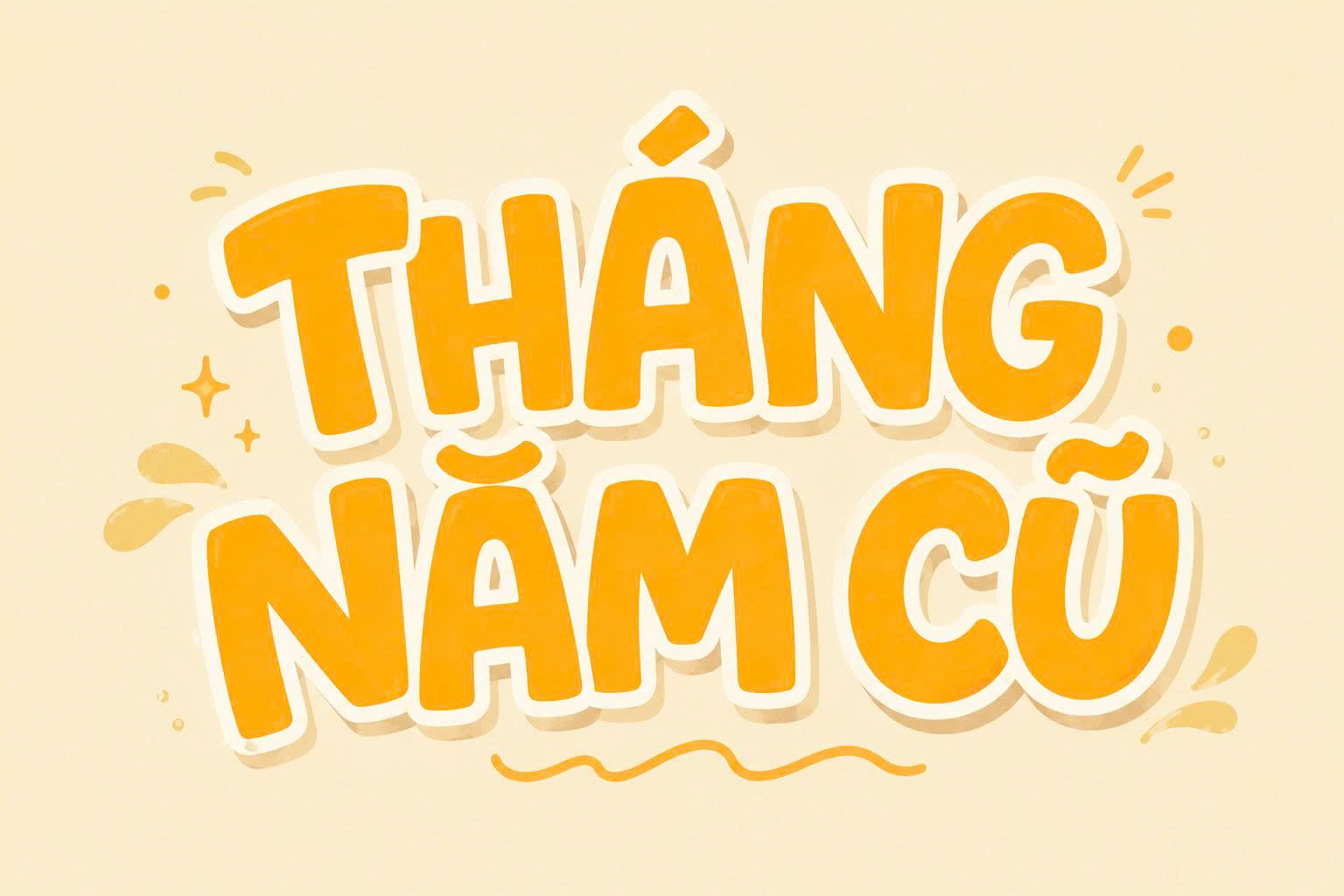
Lưu ý: Font mùa hè thường có nhiều chi tiết uốn lượn nghệ thuật. Khi in ấn trên các chất liệu có độ nhám cao như giấy Kraft, bạn nên kiểm tra độ tương phản màu sắc để đảm bảo các thông điệp truyền tải rõ ràng và không bị nhòe nét.
5 ứng dụng của font mùa hè Việt hóa trong thiết kế và in ấn
Với phong cách trẻ trung, tươi sáng và giàu năng lượng, font mùa hè Việt hóa phù hợp với nhiều thiết kế bao bì, quà tặng và ấn phẩm truyền thông theo chủ đề du lịch, nghỉ dưỡng:
- Thiết kế bao bì thực phẩm và đồ uống mùa hè: Font mùa hè phù hợp để thể hiện tên sản phẩm trên nhãn trà trái cây, nước giải khát, bánh kẹo hoặc thực phẩm đóng gói, giúp thiết kế trở nên sinh động hơn.
- Sản xuất quà tặng du lịch doanh nghiệp: Các slogan ngắn sử dụng font mùa hè khi in trên bình giữ nhiệt, túi vải canvas, nón hoặc vật phẩm sự kiện giúp bộ quà tặng mang phong cách trẻ trung, phù hợp với hoạt động team building.
- Trang trí backdrop và banner sự kiện ngoài trời: Định dạng vector giúp font mùa hè giữ được đường nét rõ ràng khi phóng lớn trên backdrop, bảng hiệu hoặc khu vực check-in sự kiện.
- Thiết kế thiệp mời và voucher mùa hè: Những kiểu chữ mang cảm giác phóng khoáng, vui tươi phù hợp với thiệp mời du lịch, chương trình ưu đãi nghỉ dưỡng hoặc sự kiện thương hiệu.
- Sản xuất tem nhãn decal sản phẩm: Font mùa hè có thể ứng dụng trên sticker, nhãn dán mỹ phẩm, đồ uống hoặc sản phẩm thủ công để tạo điểm nhấn riêng cho bao bì.
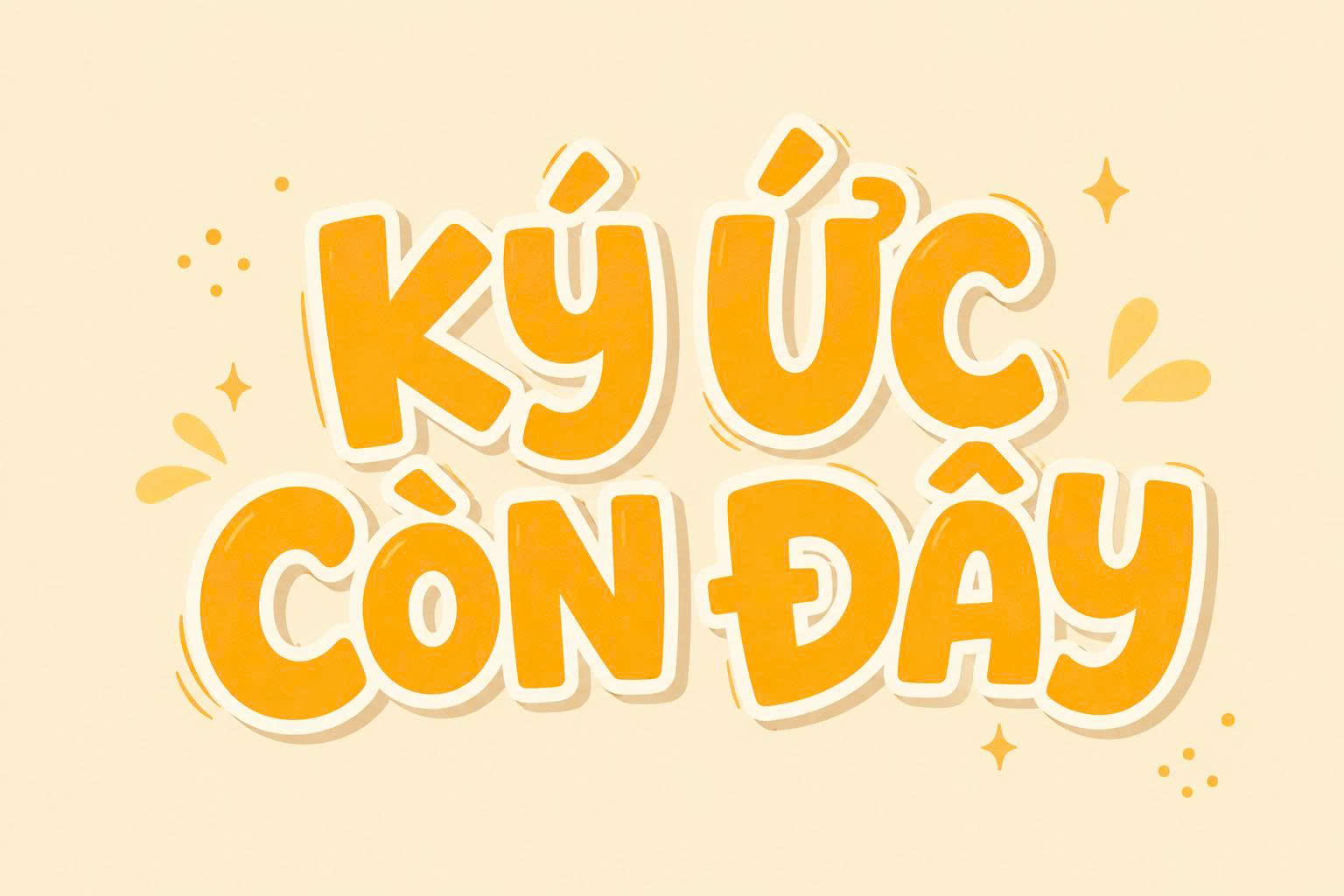
4 lưu ý khi sử dụng font chữ mùa hè Việt hóa
Để thiết kế sử dụng font mùa hè Việt hóa giữ được sự sinh động khi đưa vào sản xuất thực tế, designer cần chú ý:
- Kiểm soát độ dày nét chữ: Một số font mùa hè có kiểu chữ viết tay với nét mảnh. Khi in trên tem nhãn nhỏ hoặc chất liệu hút mực, cần điều chỉnh kích thước phù hợp để hạn chế mất chi tiết.
- Tối ưu đường Path khi gia công bế nổi: Chuyển đổi font sang dạng vector giúp xử lý các đường cong, nét chữ chính xác hơn khi thực hiện dập nổi logo hoặc slogan trên hộp quà.
- Lựa chọn màu sắc phù hợp: Các thiết kế mùa hè thường sử dụng màu sáng như vàng, cam, xanh dương. Cần kiểm tra hệ màu CMYK trước khi in để màu sắc trên thành phẩm gần với thiết kế ban đầu.
- Cân chỉnh dấu tiếng Việt: Với các font có nhiều nét trang trí, nên kiểm tra vị trí dấu mũ và dấu thanh để ký tự tiếng Việt có bố cục cân đối, dễ đọc.